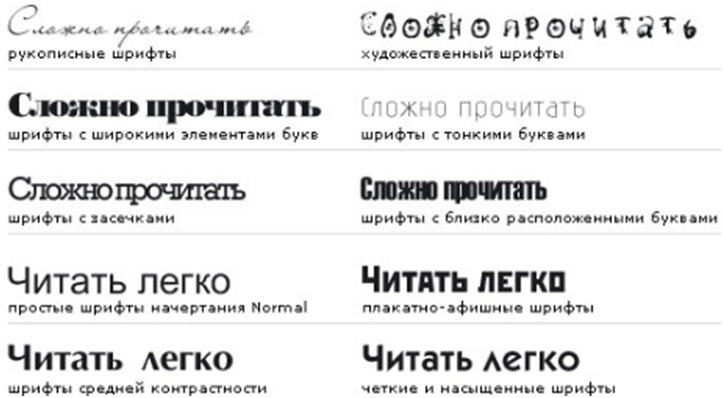
Некоторые рекомендации: шрифт следует выбирать крупный и разборчивый, чтобы его можно было хорошо воспринимать с расстояния 1-2 метра.
- Для заголовка — шрифт размером не ниже 72 пт
- Для основного текста – шрифт размером не ниже 24 пт
- Формат текста рукописи. Текст должен быть напечатан шрифтом Times New Roman, иметь размер 12 pt и междустрочный интервал 1,5 pt. Отступы с каждой стороны страницы 2,5 см. Выделения в тексте можно проводить ТОЛЬКО
курсивом или полужирным начертанием букв, но НЕ подчеркиванием.
Из текста необходимо удалить все повторяющиеся пробелы и лишние разрывы строк (в автоматическом режиме через сервис Microsoft Word «найти и заменить»).
Структура тезисов
На русском языке
- Название тезисов располагается вверху по центру листа и печатается заглавными буквами полужирным шрифтом Times New Roman 14. В конце названия точка не ставится.
- Фамилии и инициалы авторов располагаются под названием тезисов докладов, по центру относительно основного текста и печатаются шрифтом Times New Roman 12 полужирным шрифтом. В списке авторов сначала указывается фамилия, затем инициалы авторов. При необходимости надстрочным цифрами отмечаются авторы из разных организаций.
- Название организации, город, страна располагаются по центру относительно основного текста под фамилией автора и печатаются курсивом шрифтом Times New Roman 12. При необходимости цифрами указываются разные организации.
Необходимо привести официальное ПОЛНОЕ название организации. Научные руководители располагаются по центру относительно основного текста под названием организации и печатаются курсивом шрифтом Times New Roman 12.- Текст тезисов должен включать следующие разделы: введение, цель (и/или задачи) исследования, материалы и методы, результаты, выводы (или заключение).
Лучший шрифт для печатных документов
Несмотря на то, что безбумажное движение набирает обороты, все же необходимо печатать определенные документы. Листовки, брошюры, а также контракты, возможно, потребуется напечатать.